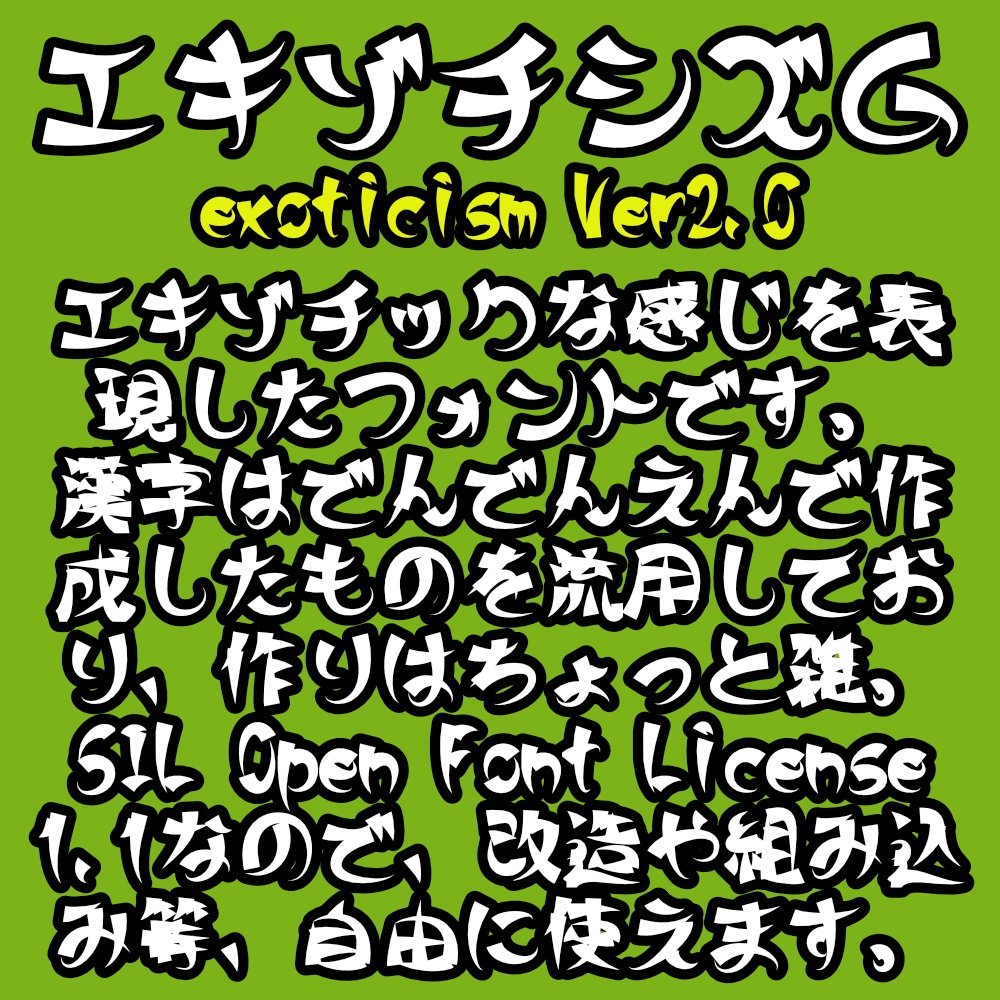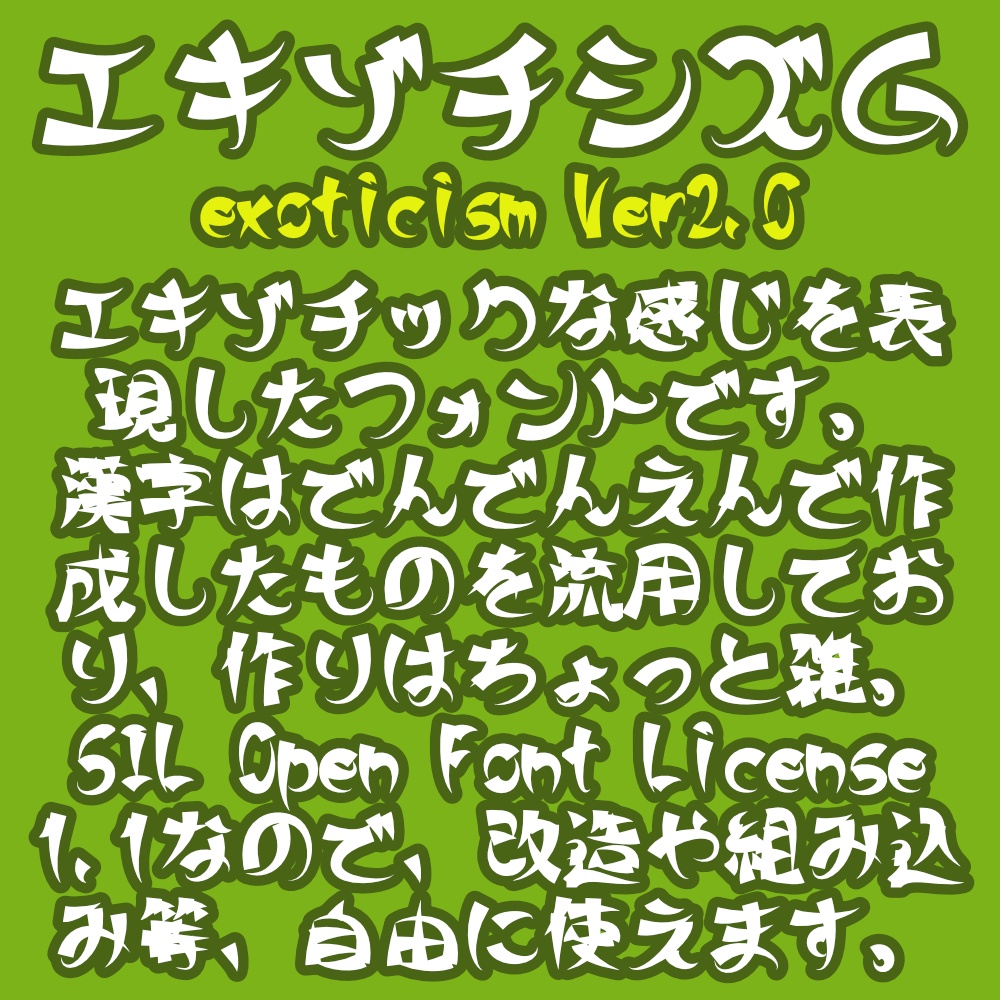
torisippoフォント エキゾチシズムDigital0 JPYFree Downloadexoticism_2.0.zip (3.21 MB)Free Downloadexoticism_1.2b.zip (57.1 KB)exoticism_2.0.zipexoticism_1.2b.zipAbout Giftスタンダードな文字を作ろうとして出来たのがこれ。 何処となくエキゾチックな感じが出てます。フォントデータ形式TrueType(.ttf)ライセンスSIL Open Font License 1.1 に準じます。更新履歴2026/06/10 v2.0 漢字と半角カナを追加し、半角英数字の幅を半分にした 2025/08/02 v1.2b readme.txtの誤記を修正 2024/11/01 v1.2a 微調整 2024/10/01 v1.2 ひらがなを追加 2024/09/30 v1.1 アルファベットと記号を追加 2024/09/27 v1.0 初版 torisippoVisit FANBOX!Fontsフォント Auxiliary line オーグジュアリラインtorisippo0 JPYFontsフォント でんでんえん/でんえんえんtorisippo1,200 JPYFontsフォント DOThoundstooth ドットハウンドトゥース(ドット千鳥格子)torisippo0 JPYFontsフォント ひらすわぷろtorisippo800 JPYFontsフォント PCB10 プリント基板配線パターンフォントtorisippo0 JPYFontsフォント MahjongMPSZColortorisippo0 JPYFontsフォント DOTjigsaw (fontforge用フォント生成スプリクト付き)torisippo0 JPYSoftwareFormat Renamer ~キーボードを極力使わないリネームソフト~torisippo1,000 JPYFontsフォント マステ丸 ラウンド25torisippo0 JPYFontsフォント ひらすわtorisippo0 JPYFontsフォント メニーワンtorisippo0 JPYFontsフォント MahjongZSPMtorisippo0 JPYFontsフォント MahjongMPSZtorisippo0 JPYFontsフォント ブルーテイルtorisippo0 JPYFontsフォント デンエンtorisippo0 JPYFontsフォント カールtorisippo0 JPYFontsフォント ウォータービーズtorisippo0 JPYFontsフォント ウーファーtorisippo0 JPYFontsフォント ラバーボールtorisippo0 JPYFontsフォント フォースフルドットtorisippo0 JPYSee More